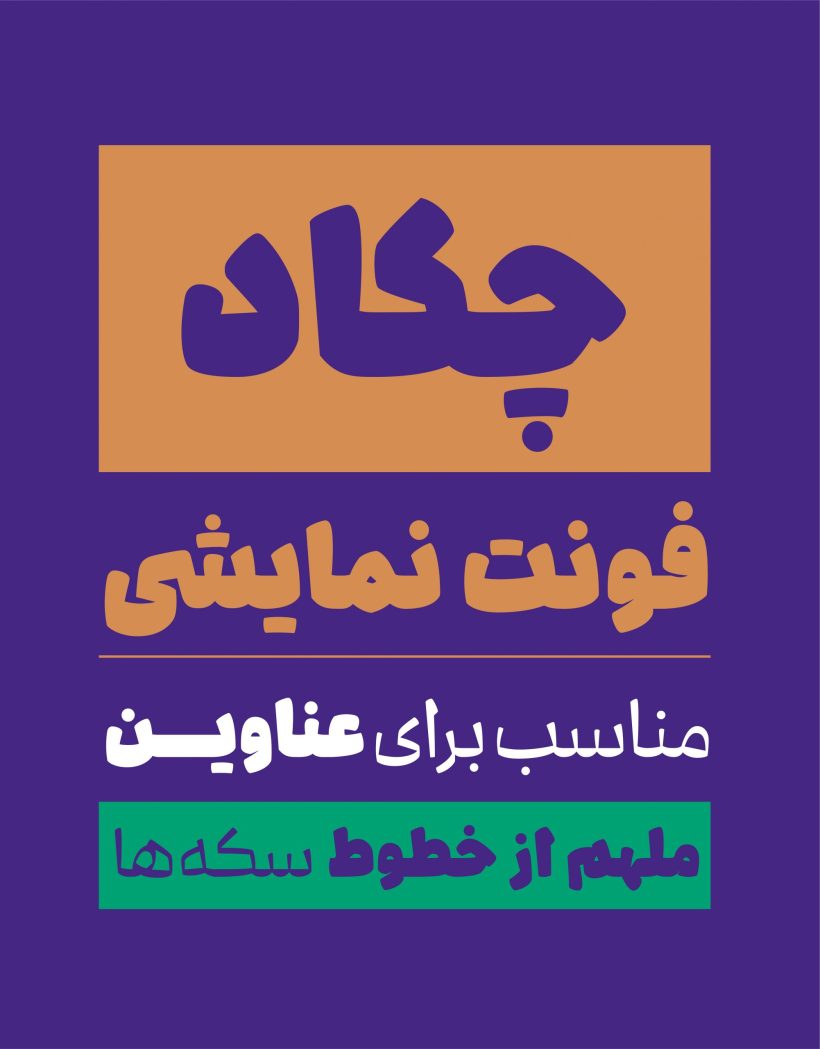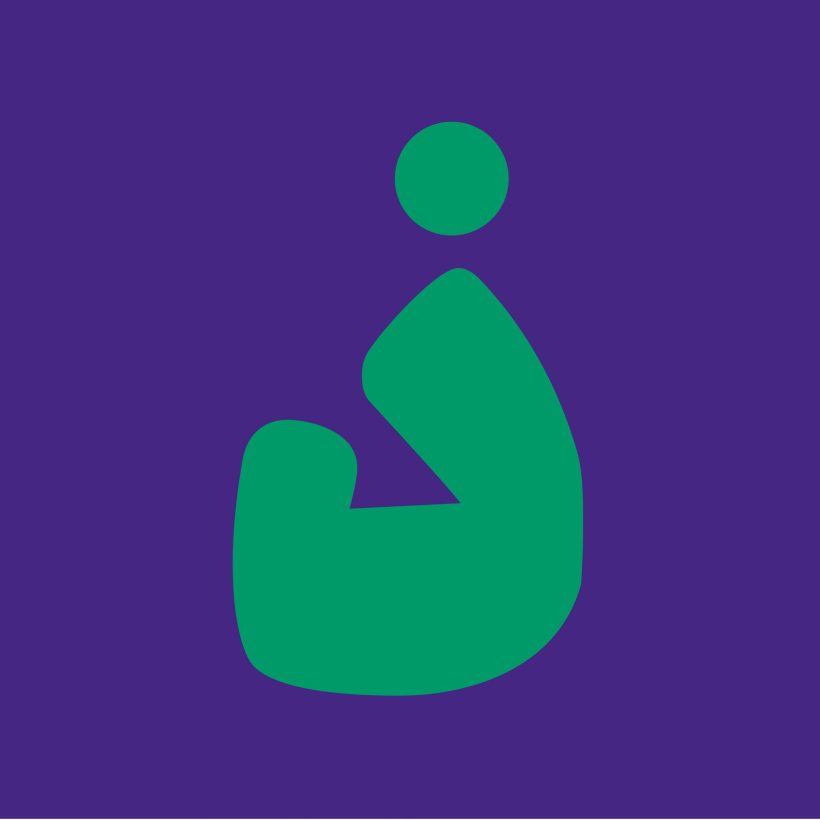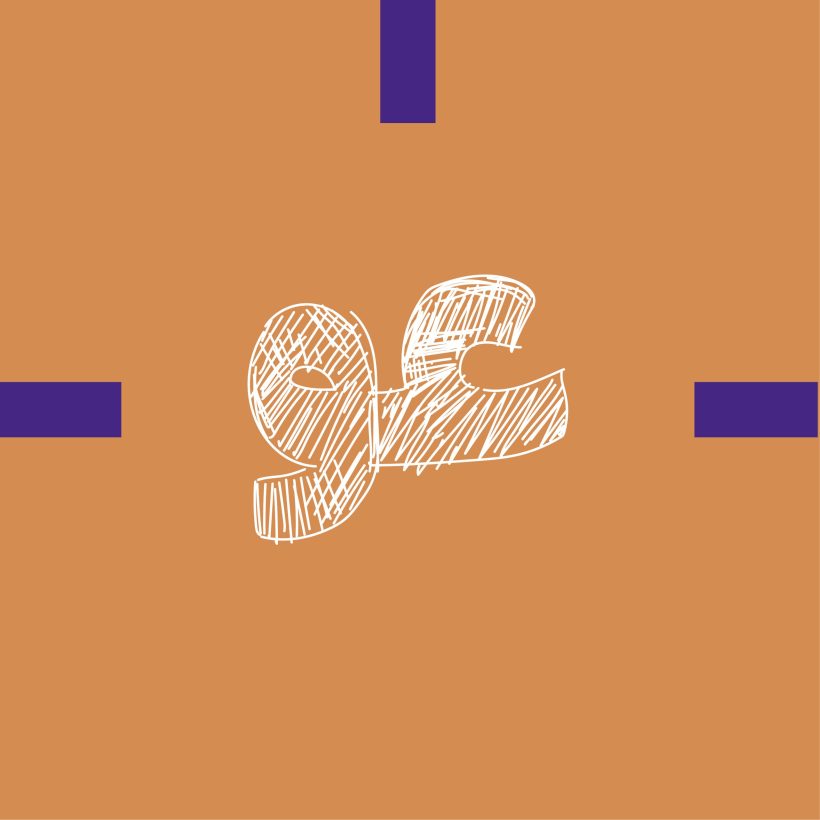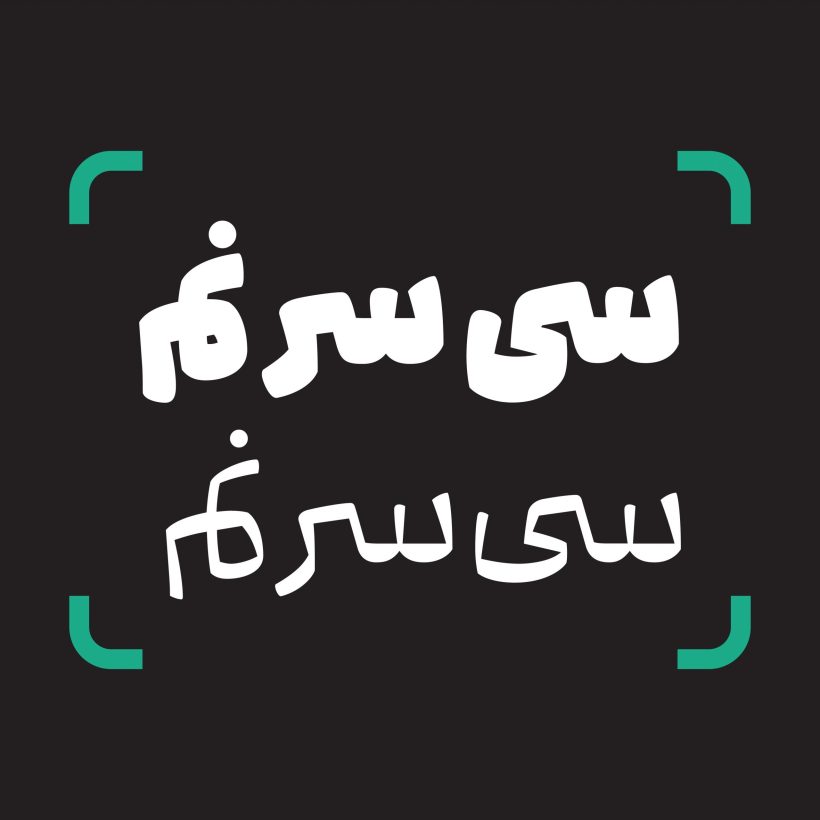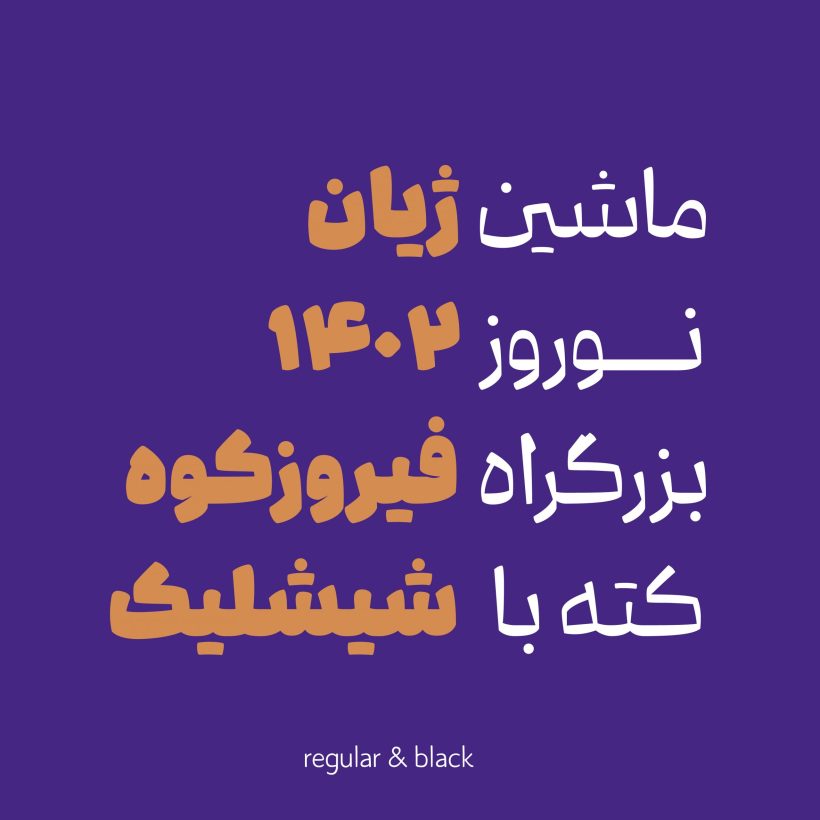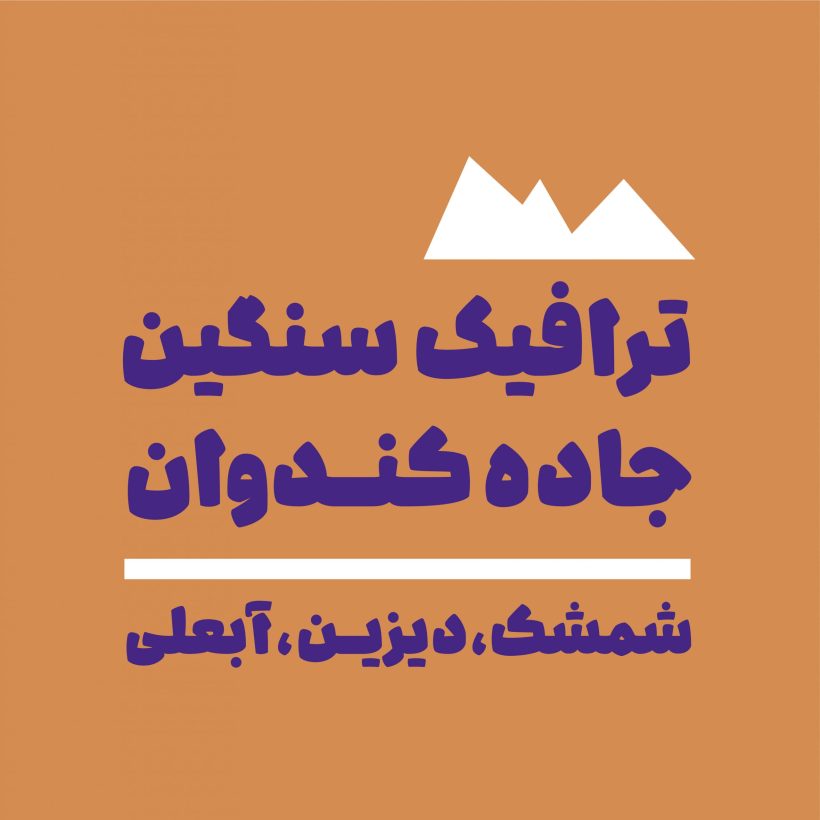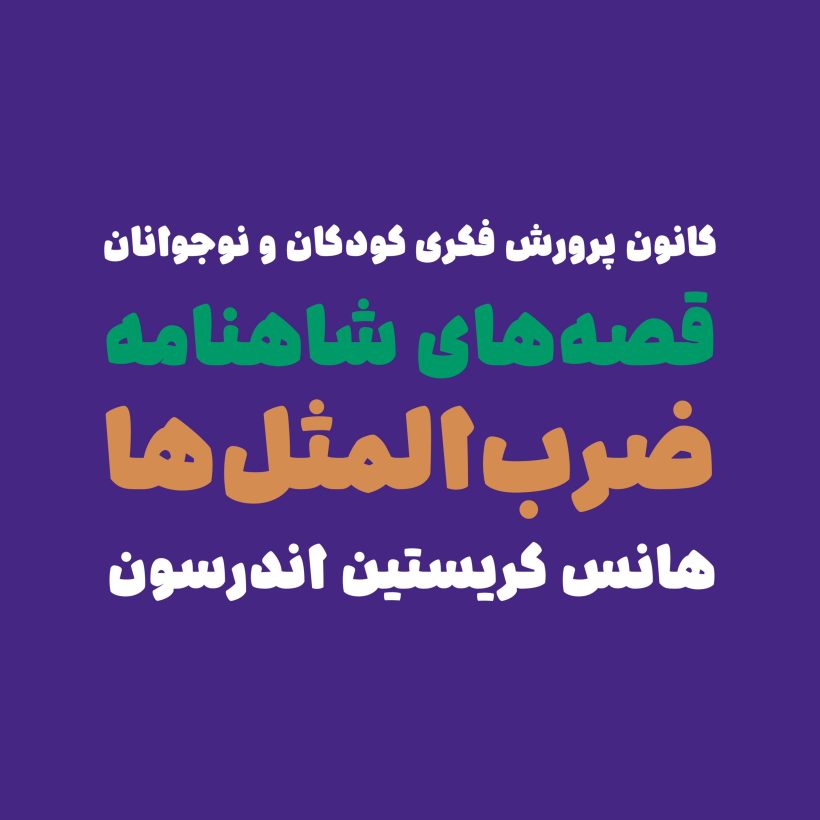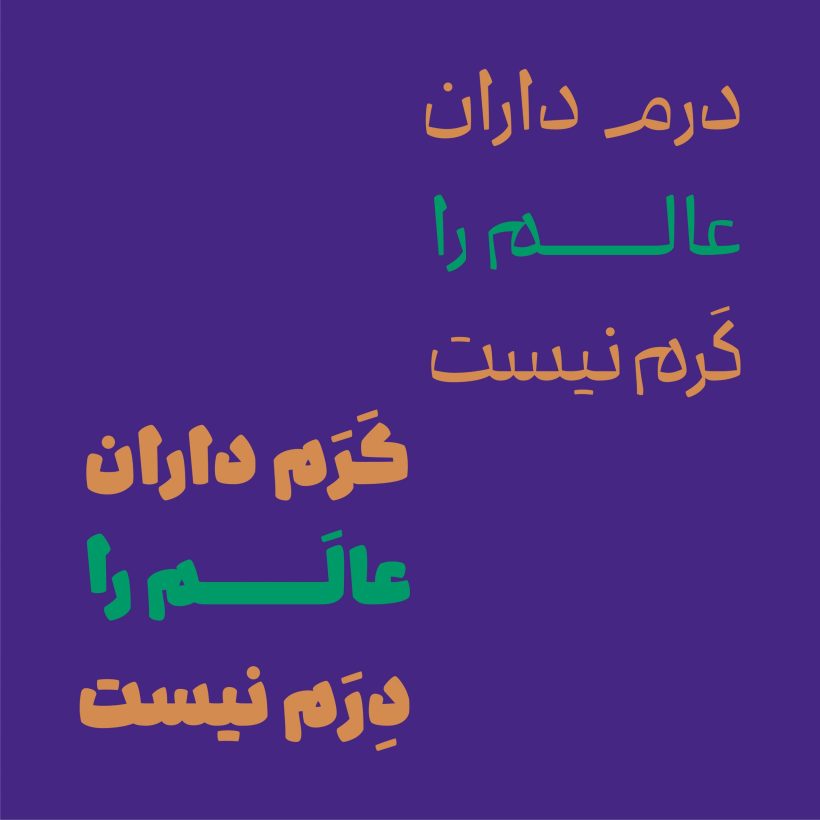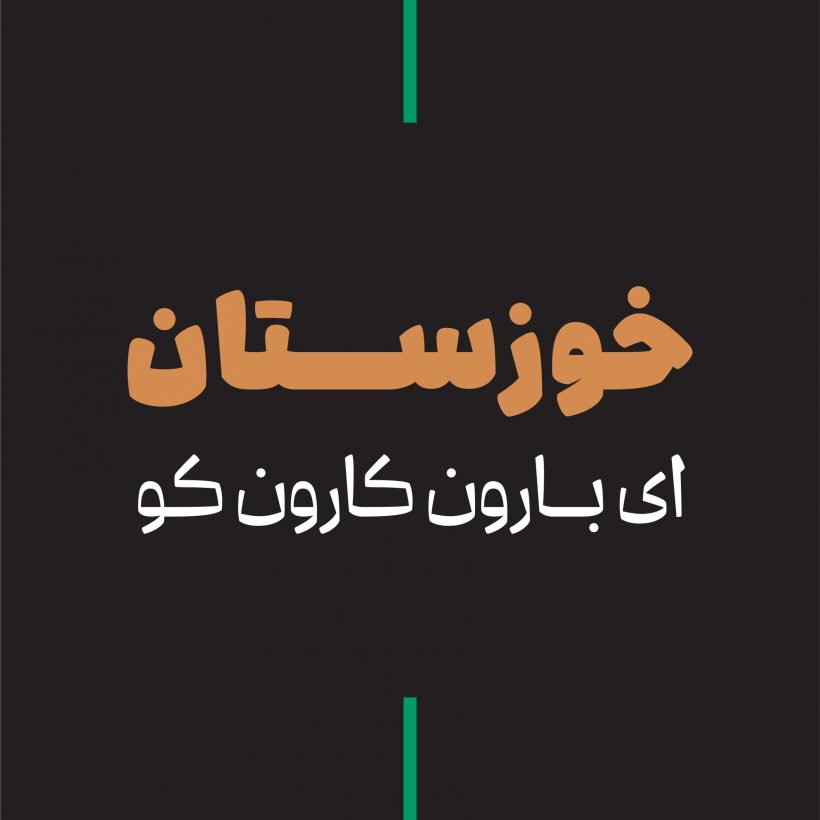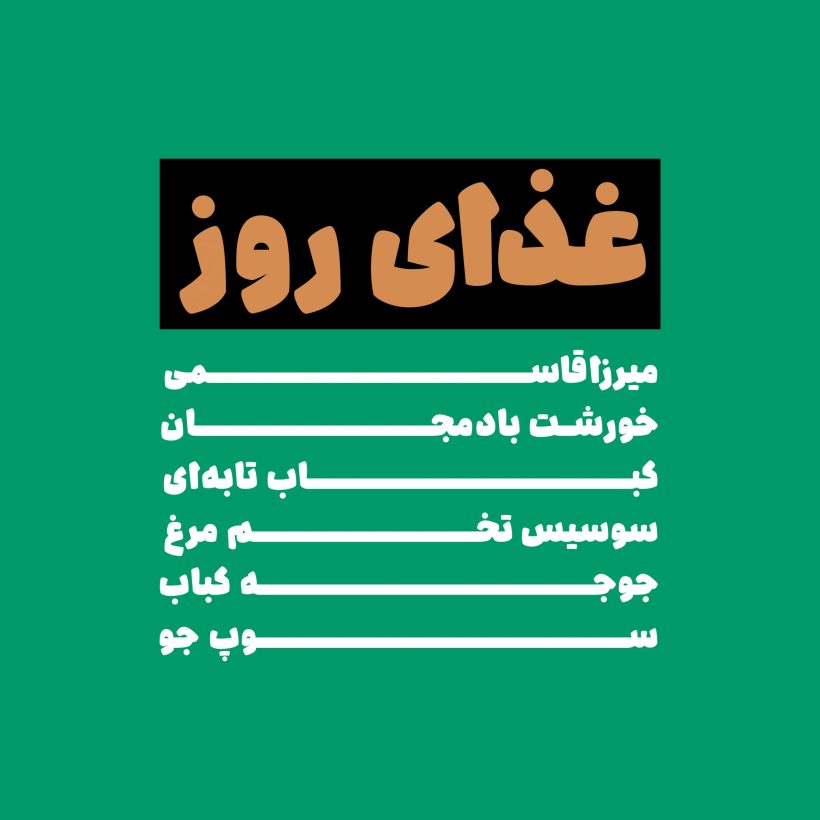
فونت چکاد
فونت چکاد با الهام از خط سکه نقره شاه اسماعیل اول محفوظ در کتابخانه ملک طراحی شده است. چکاد فونت نمایشی و در دو وزن معمولی و بلک است و برای عناوین و عبارت های کوتاه کاربرد دارد. فونت چکاد دارای لحنی صمیمانه و غیر رسمی است و تلفیق همزمان حرکات مدور و هندسی، لحنی پویا و صمیمی را تداعی می کند. در فونت چکاد ضمن حفظ قواعد تناسبات اندازه خوشنویسی تلاش شده تا حد ممکن حروف به صورت جمع و جور و با فضای منفی فشرده طراحی گردد.
قواعد کرنینگ و اعراب گذاری ها در فونت چکاد به کار رفته است. چکاد دارای لیگیچر و کارکترهای جایگزین است تا برحسب نیاز و برای زیبایی بیشتر انتخاب شود.